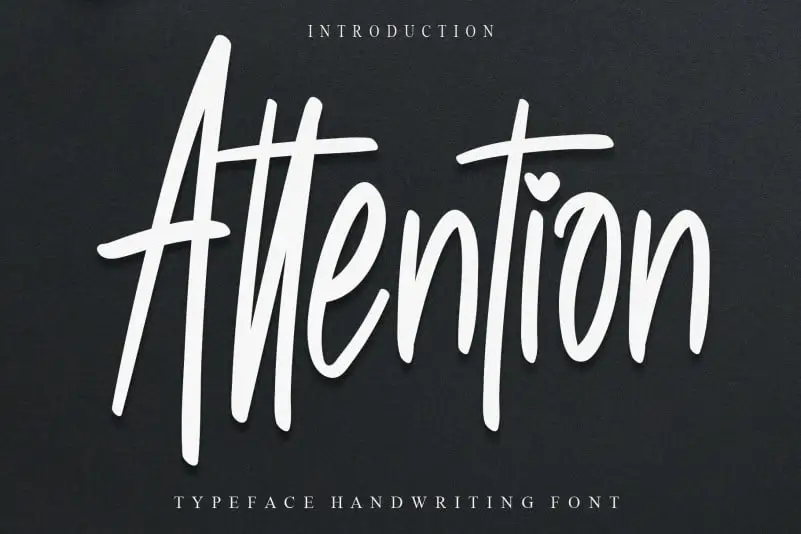
Attention Script Font – Download Grátis
A atenção Script Font é uma escolha perfeita para quem deseja adicionar um toque autêntico a suas obras digitais ou impressas. Feita pela criativa equipe da CreativeLetter, essa fonte de escrita cuidadosamente elaborada oferece o tipo exato que você está procurando – uma mão que escreve a sua mensagem com estilo único. Com traços suaves e linhas fluidas, ela ajuda a criar uma experiência visual enriquecedora em qualquer projeto. Seja para um design gráfico profissional ou um trabalho de arte criativo, essa fonte atinge o equilíbrio perfeito entre personalidade e funcionalidade. Aproveite esta oportunidade especial de experimentar algo novo e incrivelmente diferenciado na sua próxima criação visual.